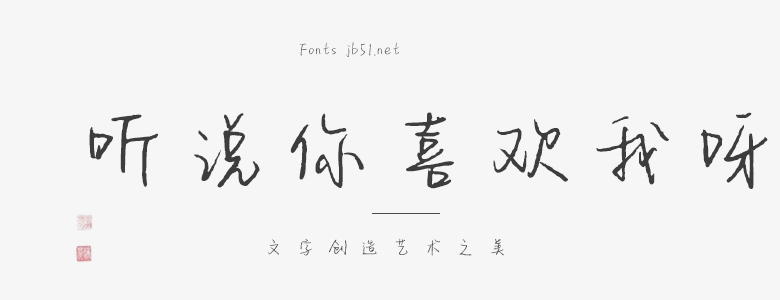
“聽說你喜歡我呀”這款字體設(shè)計獨特,充滿了浪漫和趣味性。字體設(shè)計以手寫風(fēng)格為主,線條流暢自然,給人一種親切和溫暖的感覺。每個字母都帶有一種俏皮的態(tài)度,仿佛是戀愛中的呢喃,讓人不禁想起那些甜蜜的時刻。 “聽說你喜歡我呀”字體的筆畫細(xì)節(jié)精致,字母間緊湊而協(xié)調(diào)。整體風(fēng)格簡潔而不失個性,既適合表達(dá)浪漫的情感,也適合在各種場合使用。同時,這款字體還具有良好的可讀性,無論是在印刷品還是電子設(shè)備上都能清晰地呈現(xiàn)。 總之,“聽說你喜歡我呀”字體不僅充滿了個性和浪漫,還能在不同的情境中表達(dá)出深情和溫馨。它將是一種具有吸引力的選擇,適用于各種文字設(shè)計和印刷品制作。